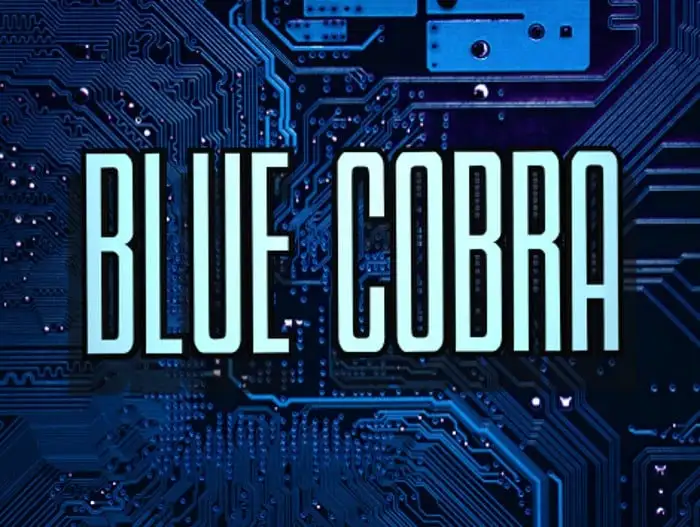
Blue Cobra Display Font – Download Grátis
A Blue Cobra Display Font é uma seleção única de 32 versões que oferece uma ampla gama de opções para personalizar seu design. Essas variações, incluindo Regular, Italic e suas variantes alternativas, foram projetadas para adaptar-se a diferentes estilos e usos. Com uma paleta tão diversificada, essa fonte exibe uma versatilidade que permite você escolher o formato perfeito para seu projeto. Seja ela em um tom sólido ou com um contraste vibrante, a Blue Cobra Display Font está aqui para enriquecer sua composição visual de maneiras impressionantes e únicas. Com tamanhos de fonte reduzidos e aumentados, incluindo Condensada e Expandida, bem como formatos que destacam ainda mais o texto, esta é uma escolha versátil para qualquer projeto onde você deseja destacar os detalhes em sua designação.